Ieri abbiamo visto alcuni splendidi esempi di loghi progettati ad arte. Oggi invece vogliamo focalizzare l’attenzione su un aspetto fondamentale per qualsiasi progetto di marchio/logotipo abbiate in mente. La scelta del font. Un operazione che può portare via molto tempo e essere soggetta a continue prove e ripensamenti.
Per questo oggi vi proponiamo una serie di ottimi font vintage gratuiti tra cui scegliere per sviluppare il vostro prossimo progetto.
Old Sans Blank
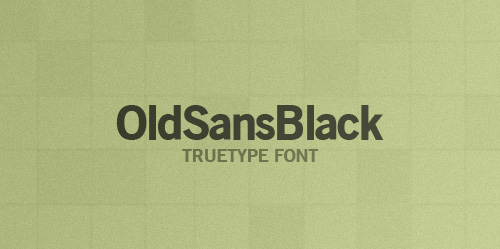
Hit the Road
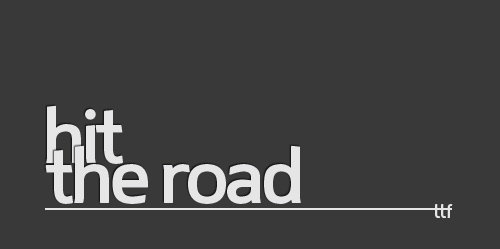
Lobster
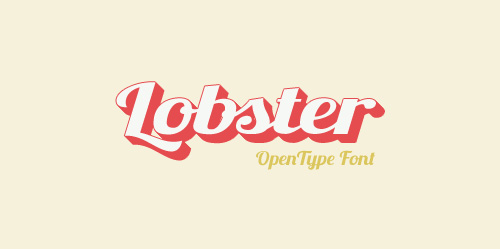
Days
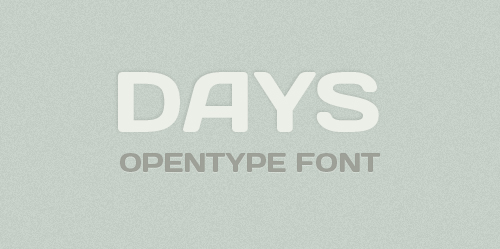
Fletcher Gothic
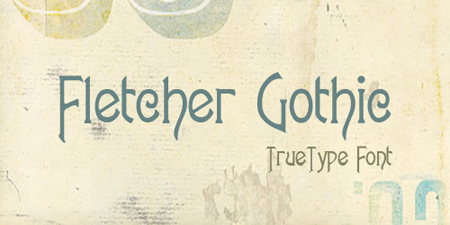
Deftones stylus